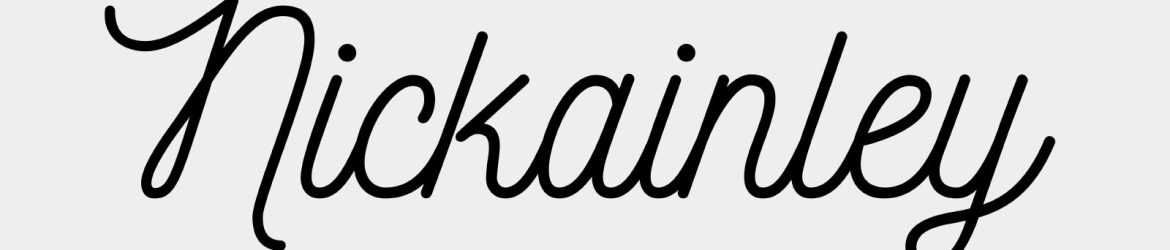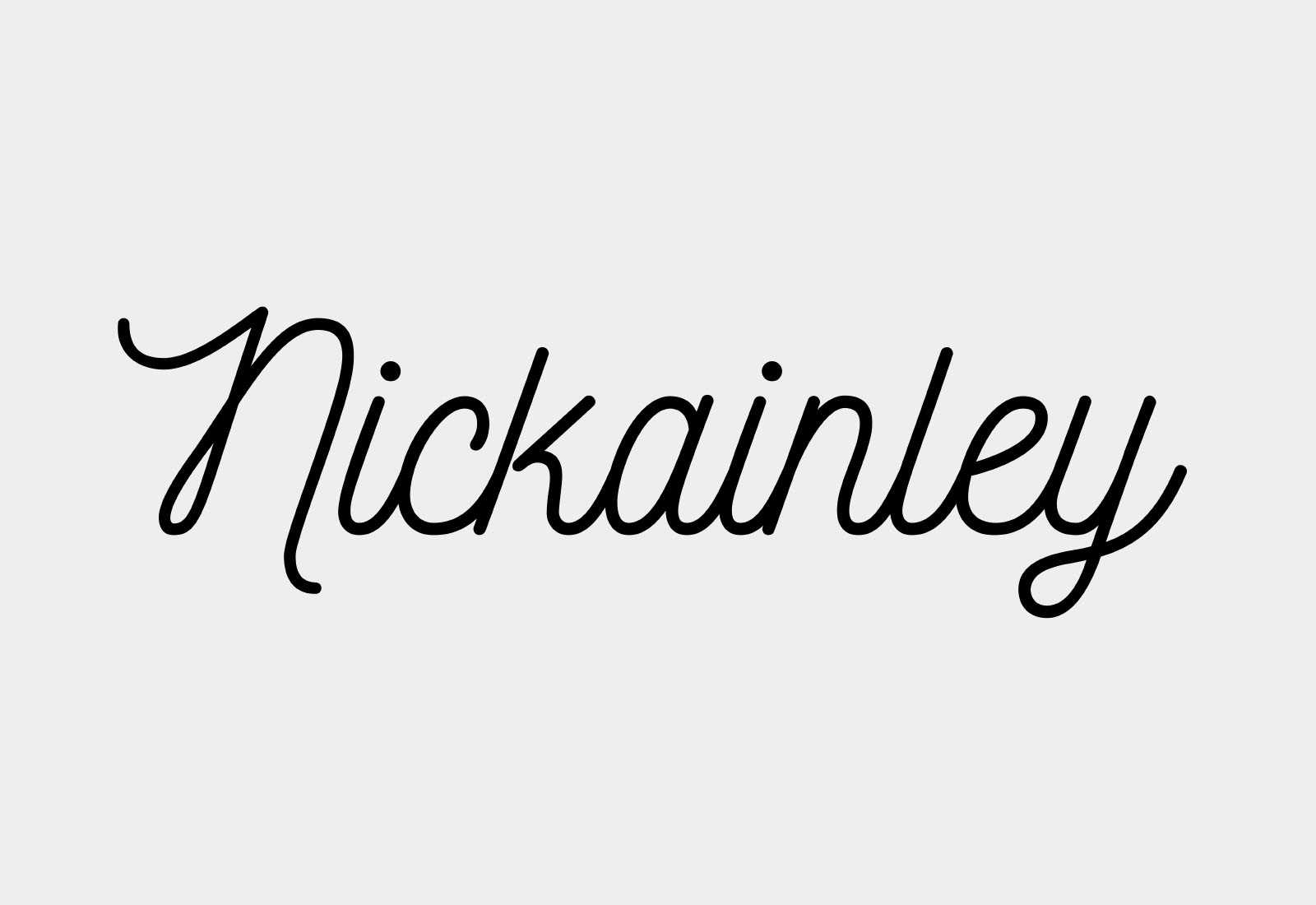
Nickainley Free Monoline Typeface
Nickainley é uma fonte de tipo monoline que está ganhando popularidade entre os designers. Suas linhas simples e unificadas criam um estilo limpo e único, oferecendo um toque elegante quando usadas em combinação com outros tipos de fontes. Nickainley é uma fonte tipográfica de script com um toque clássico e vintage. Está disponível tanto em letras maiúsculas quanto em minúsculas, e inclui sinais de pontuação, números e caracteres especiais, tornando-o um recurso de fonte perfeito para aplicações diversas como badges, assinaturas, materiais de propaganda e identidade visual. Nickainley foi criado pelo Senior Studios, uma foundry localizada na Indonésia, e agora está disponível para a comunidade de design. Se você quiser explorar mais o trabalho desta equipe, você pode visitar seu portfólio. Nickainley é um recurso de fonte maravilhoso e prático que pode agregar ao seu projeto.